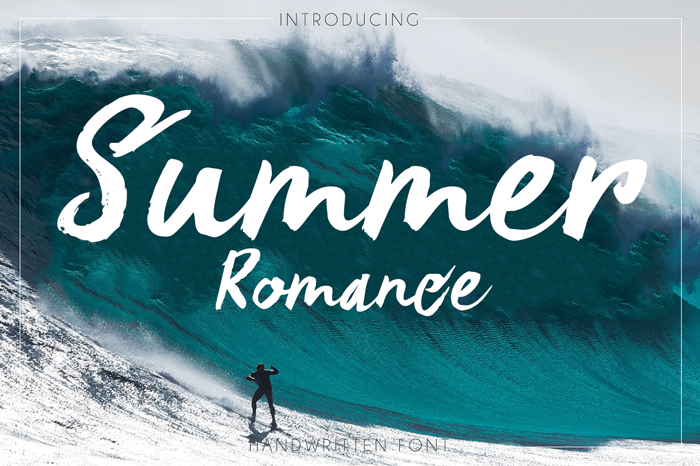
Summer Romance Font
A Summer Romance Font é uma elegante tipografia feita inteiramente à mão com um canivete de calligrafia japonesa. Esta nova opção do tipo vem para a família do Hanoded, apresentando-se como uma delicada fóntica conectada em script que combina as marcas mais românticas da Carpe Noctem com o frescor das estações primaveris e verões. A Summer Romance é perfeita para aplicar em capas de livros românticos, produtos de beleza e websites de viagens promovendo passeios românticos, pois seu charme natural se adapta a tudo. Sem dúvida, uma fonte que vai adicionar um toque especial à sua próxima criação gráfica.